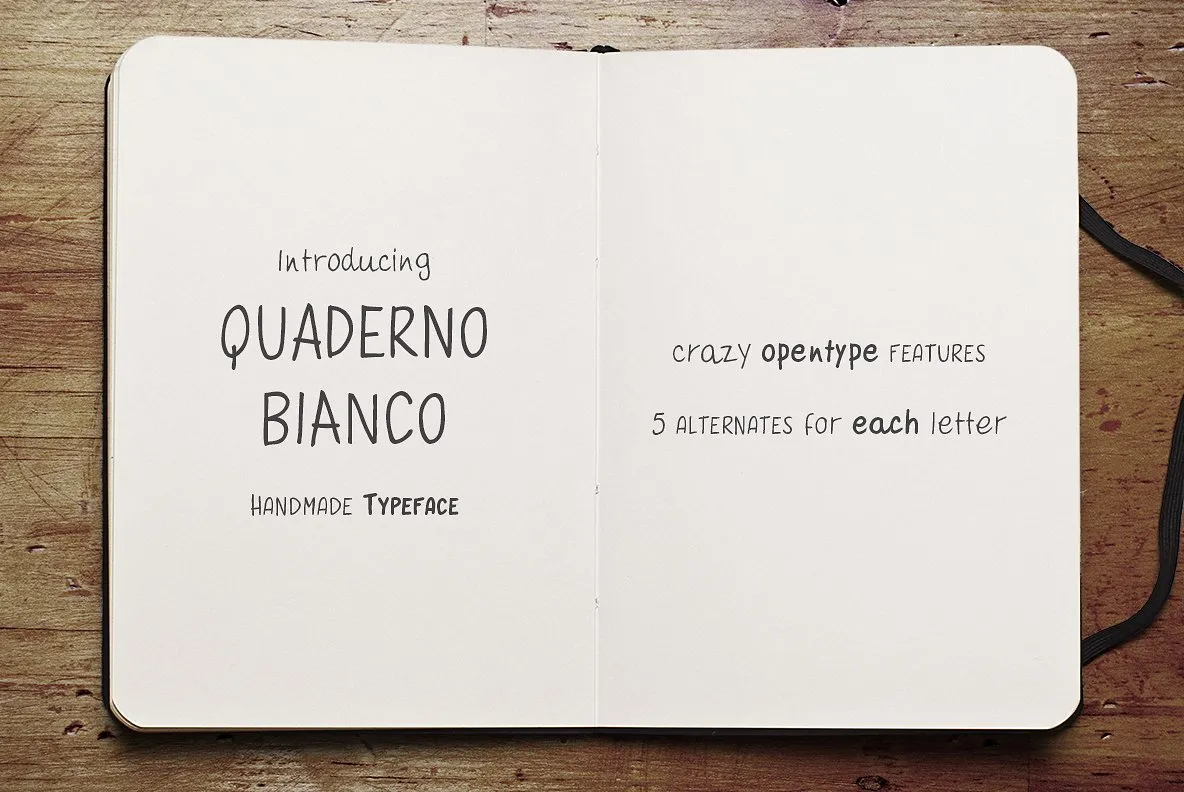
Quaderno Bianco Font Family – Fonte Grátis
Quaderno Bianco Font Family
Quaderno Bianco é uma fonte de escrita que evoca a sensação de uma anotação rápida deixada à mesa ou em um adesivo no frigorífico, simples e instintiva, como se tivesse sido salva pelo último pensamento inesperado. O nome “Quaderno Bianco” remete exatamente a este conceito: o diário da sua criatividade. Este design abraçador e intuitivo oferece uma variedade única de opções para quem busca expressar-se de maneira natural e sem restrições. Os recursos especiais, como a função SmallCaps e a Random, permitem que cada letra possa se manifestar em quatro versões distintas, cada uma com detalhes sutis que trazem à vida o seu design único. Esta fonte é perfeita para comunicadores positivos, tanto na criação de identidades corporativas quanto nas propagandas e anúncios para produtos bio ou energia renovável. As suas formas simples e dinâmicas permitem uma expressão fluida em cartazes, cartões de felicitações e outros meios onde a criatividade é vital. O “Alternate” Opentype faz da Quaderno Bianco uma fonte segura para qualquer projeto que exija uma grande variedade de opções e adaptabilidade, garantindo sempre uma solução para os mais variados usos e situações.
Designer: Monofonts